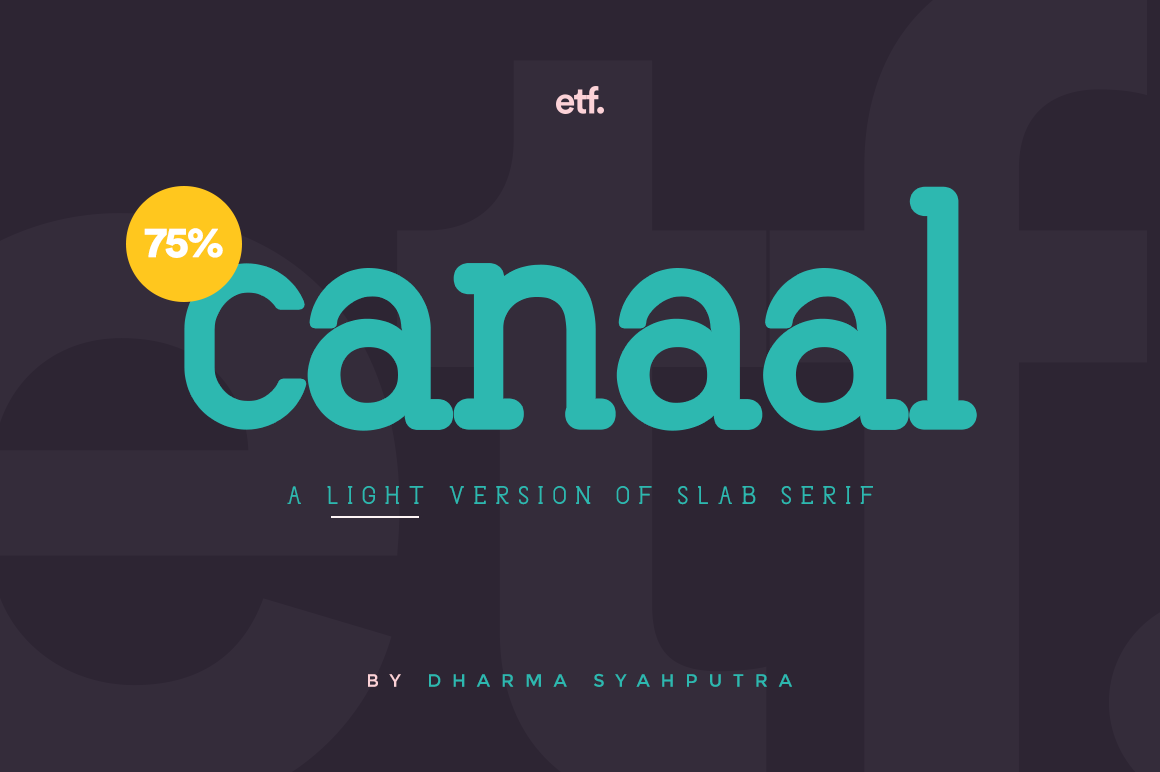
Canaal Slab Light Font – Download Grátis
A Canaal é uma fonte que se torna imediatamente reconhecível pela sua simplicidade elegante em minúsculas e robustez sofisticada em maiúsculas. Quando aplicada a letras mais grandes, como títulos ou headlines, ela ganha um toque poderoso e envolvente. O design desta fonte combina linhas marcantes e ângulares com formas arredondadas de uma forma que cria um ambiente acolhedor. Os designers podem se sentir completamente satisfeitos ao usá-la em suas criações, seja para criar materiais visuais profissionais ou simplesmente expressar seu estilo pessoal de maneira autêntica e única. Seja você um designer gráfico experiente ou iniciante, a Canaal é uma fonte que se destaca por sua simplicidade envolvente.